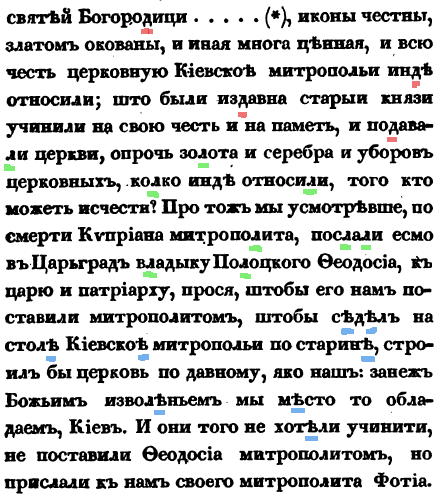
[kyrillisch] Gesucht: Font für OCR-Training
Um Tesseract für einen größeren Einsatz zu trainieren, benötige ich eine dem Input möglichst ähnliche Vorlage. Im Anhang findet sich ein mit Markierungen versehener Auszug. Die Probleme sind, soweit bisher ersichtlich, sind:
• Das idiosynkratische „д“, welches oben spitz zuläuft und mit einer verhältnismäßig langen Serife nach links versehen ist (rote Markierungen);
• das sehr schmale „л“, das zum Teil bloß über das linke Tröpfchen erkennbar ist (grün);
• das niedrige „ѣ“ (blau).
Zudem stammen die Texte aus der Zeit vor 1917 (das Beispiel ist von 1846), weshalb zumindest das Jat und „і“, wenn möglich auch „ѳ“ und „ѵ“ vorhanden sein sollten.
Ich habe bereits alle mir verfügbaren Kandidaten dagegengeworfen, mit geringem Erfolg. Damit ich mich auf das Resultat verlassen kann, hätte ich angesichts der streckenweise äußerst unscharfen Vorlage aber gern eine möglichst passende Schriftart. (Am Original zu trainieren ist dann doch etwas zu haarig …)
Ich hab zwar keine Ahnung von kyrillischen Texten, aber als Klarstellung für eventuelle Kenner wäre eine Bestätigung meiner Vermutung ganz praktisch:
Falls ich das jetzt richtig verstanden hab, suchst du eine Schriftart, die möglichst alle erwähnten Zeichen hat und der aus deiner Abbildung möglichst ähnlich ist. Damit willst du dann die Texte in besserer Qualität setzen, um daraus generierte Bilder einem OCR-Programm als Training vorzusetzen. Endziel ist dann vermutlich, die alten Dokumente zu digitalisieren.
Old Standard und Tempora? Hatte ich bereits getestet, sie erfüllen die Kriterien nicht oder nur teilweise.
Mein erster Trainingsdurchgang mit Paratype Serif war übrigens eine Niete: selbst die im Prinzip ungeeigneten Defaults für Ukrainisch liefern noch brauchbarere Ergebnisse … sieht so aus, als müßte ich doch Hand anlegen und am Original trainieren.
zumindest unter freien fonts wüsste ich nichts geeignetes. du könntest aber den font des originals digitalisieren ;) da könnten dann eventuell auch andere davon profitieren ;)
Die Scotch Modern entspricht dem Stil Deines Beispiels und enthält auch kyrillische Zeichen, ist aber eine freie Neuschöpfung, also keine genaue Digitalisierung einer Bleisatzschrift.
Danke für den Nachtrag. Ich bin mittlerweile beim zweiten Trainingsdurchlauf mit zusammengeklaubten Textschnipseln aus dem Zieltext. Etwas Aufwand wird mir vomCowboxer[1] abgenommen, insgesamt ist diese Art „Reverse Typographie“ aber recht mühselig.
Die Scotch ist in der Tat eine Überraschung, vor allem in Sachen Unicode-Abdeckung, wo sie fast mit CM-Unicode mithalten kann. Prächtige Schrift, wird beim nächsten Lottogewinn als erste gekauft werden … danke für den Link!